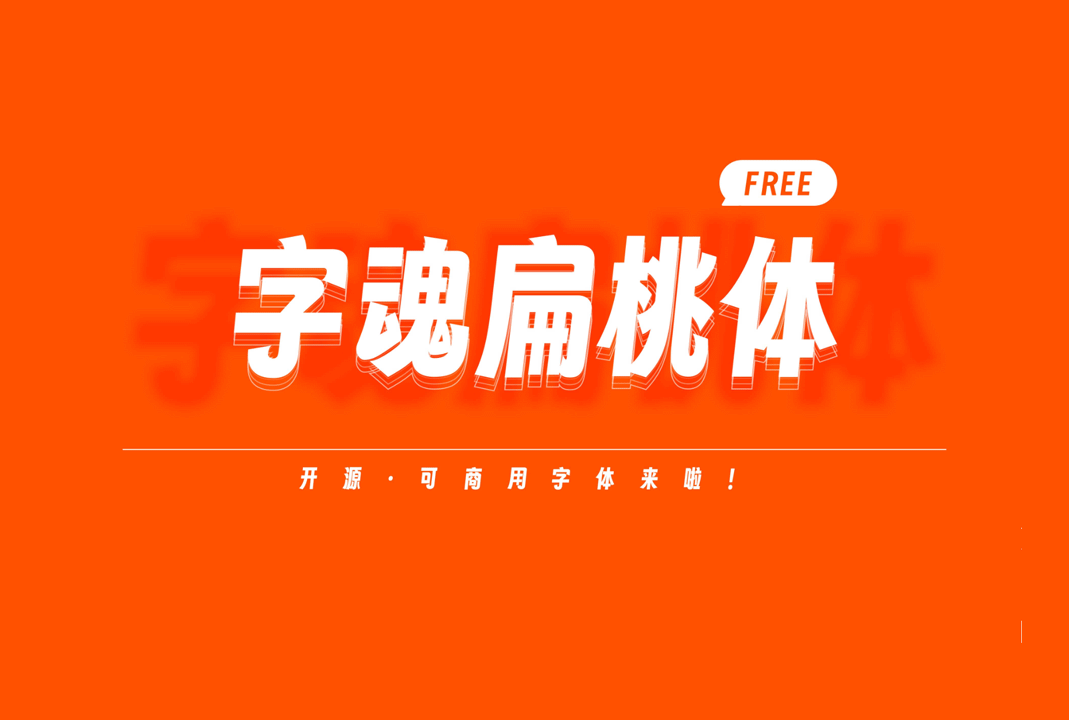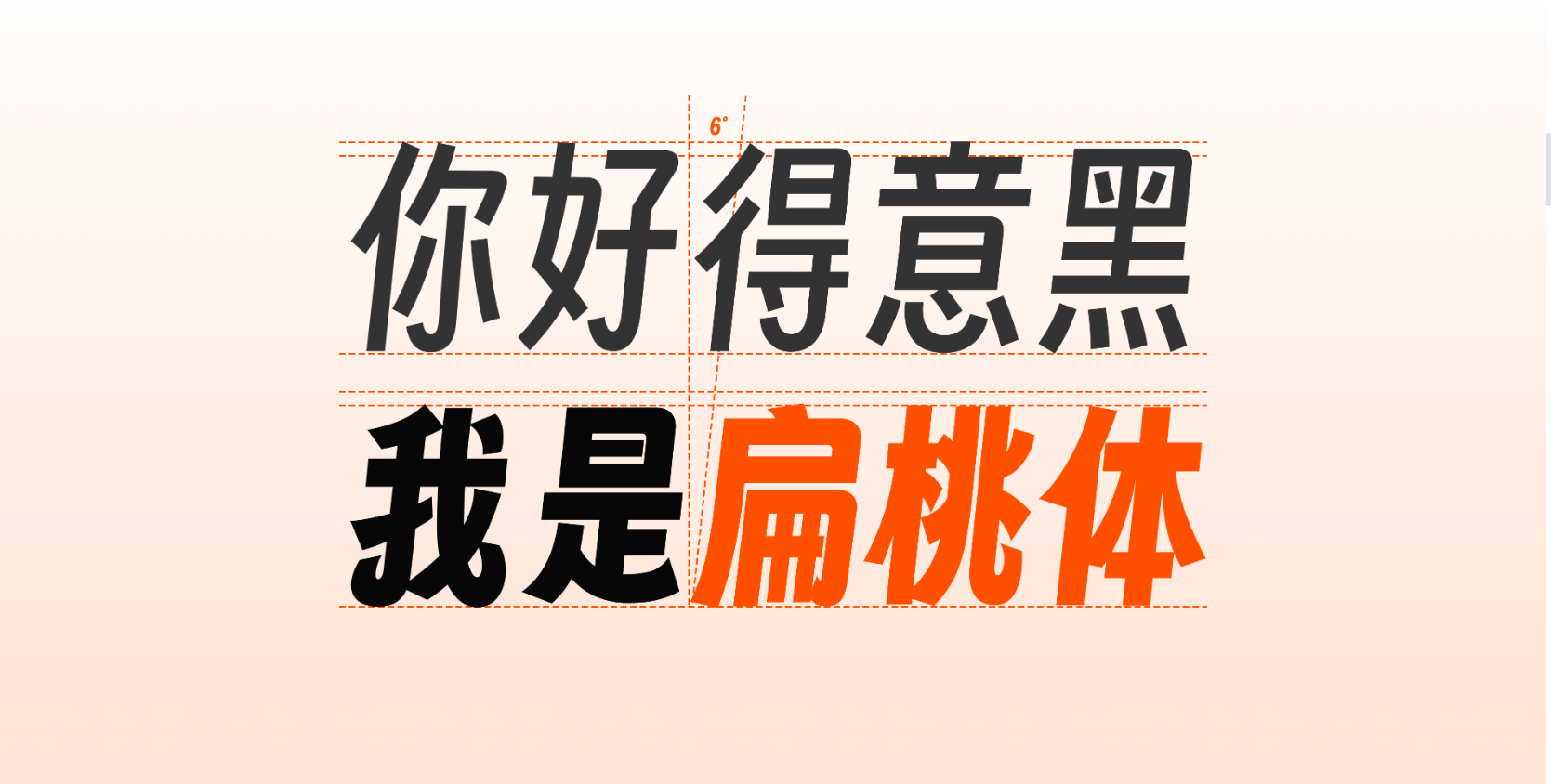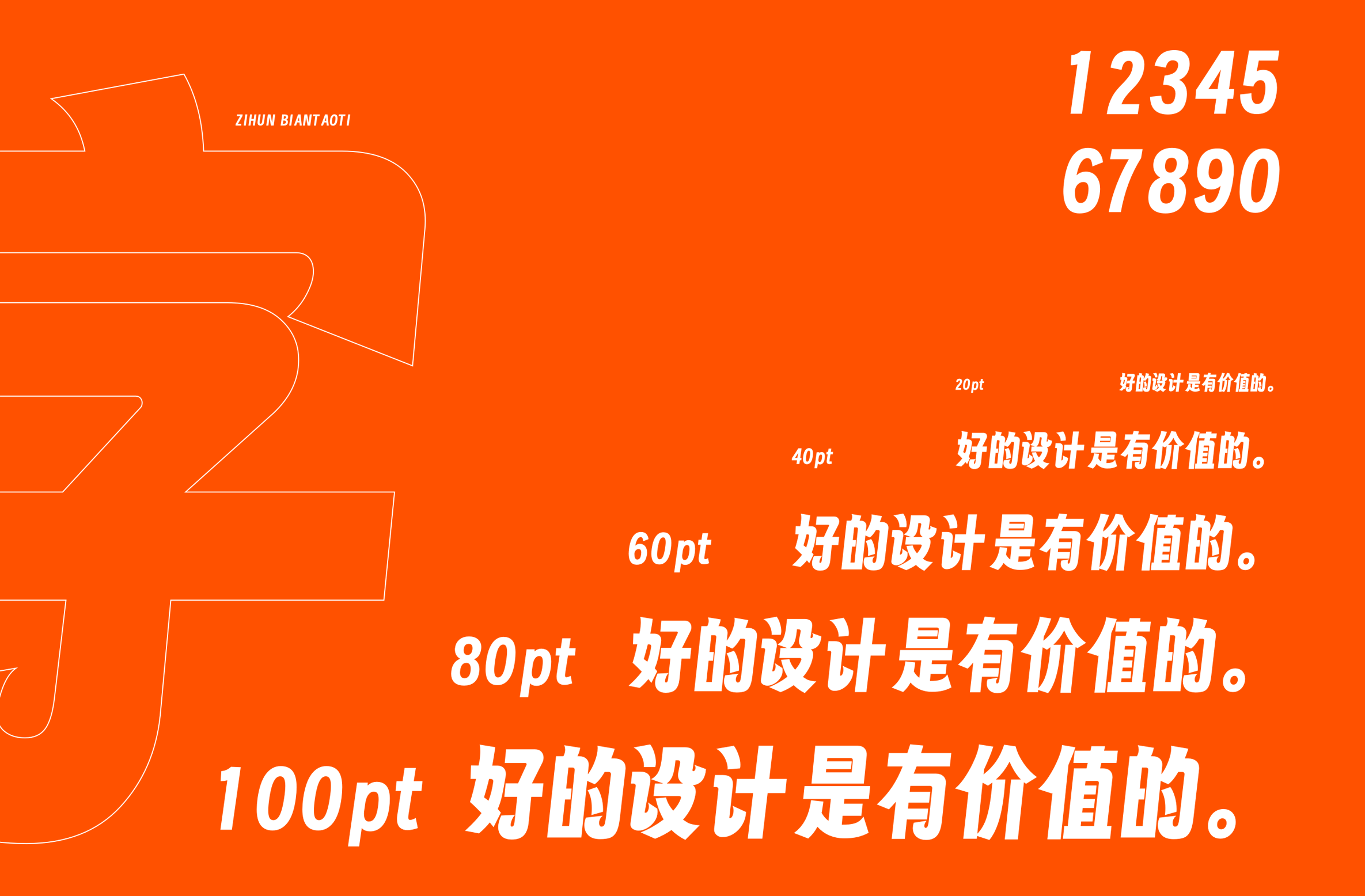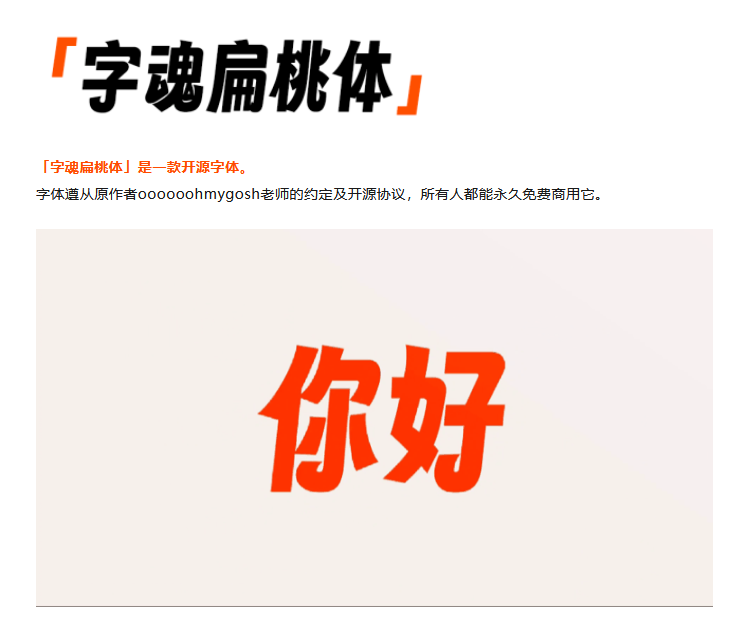
字魂扁桃体是字魂网对开源字体 得意黑体(Smiley Sans)进行二次创作后发布的免费商用字体,于微信公众号与官网声明可以开源免费商用。
# 得意黑体(Smiley Sans)是由B站 oooooohmygosh 老师与锚钨团队发布了免费商用字体,以 SIL Open Font License(OFL 1.1) 协议开源。